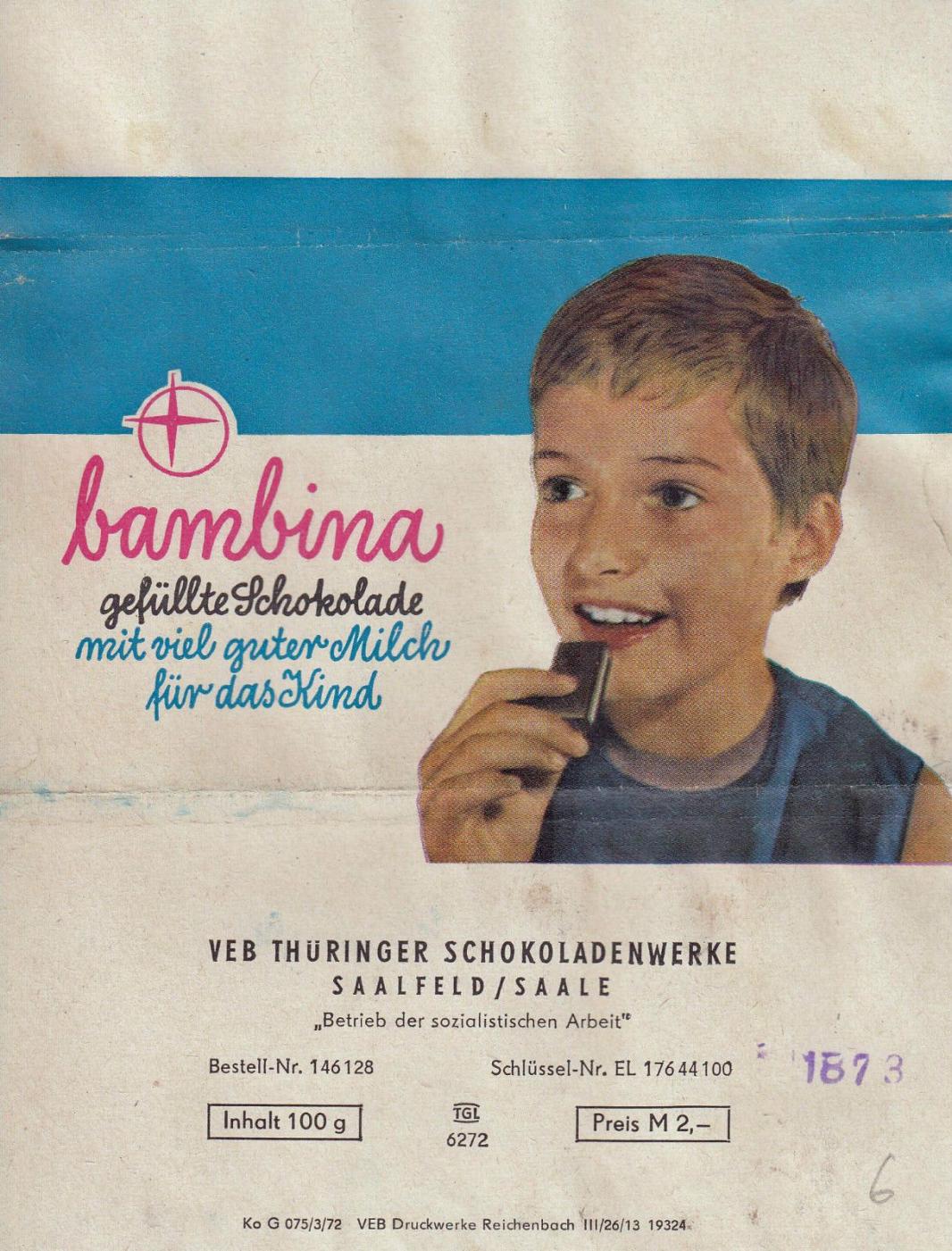
Tafelwerk DDR (Verlag Volk und Wissen)
ganze Arbeit! Und schön, dass es auch kyrillische Zeichen gibt.
Das ist richtig. Nur sah es eben zu beginn mit der Tafelwerk so aus, als habe es die Scvhrift nur als Fotosatz gegeben, und dann hat sich eben die Mode derart geändert, dass solch typische 70er kaum digitalisiert wurden. Natürlich kommt das in die Schrift.
Und wenn Sie mir da beim Kontakt behilflich sein könnten, wär das Schön. Den vorgeachlagenen Copyright-String habe ich jedenfalls schon mal genau so eingefügt und mit dem Einbau auf die Website warte ich natürlich auch noch.
Auch der Fontname steht durchaus noch zur disposition, Tafelwerk war ja mehr als Arbeitstitel gedacht.
Nun, wenn die so schon fetzt, habe ich gedacht, das geht noch fetziger, mit OpenType-Funktionen zum automatischen Durchkoppeln der Worte.
Hier habe ich jetzt die Glyphen in je 4 Varianten:
Als Solozeichen ohne jede Anfangs- und Endstriche,
als Startzeichen ohne Anfangsstrich und Kopplung rechts ,
als mittelzeichen mit beidseitiger Koppelung und
als Endzeichen mit Kopplung lnks und keinem Endstrich.
Ich habe, weil ich dafür so viele rote Striche in meinen Diktaten hatte, auch i-Punkte hinzugefügt - vielleicht ergänze ich das noch als Stilvariante ohne diese - mal sehen.
Wer aber diese Anfangs- und Endstriche wünscht, wie in der Originalversion, einfach Bindestriche vor und nach dem Wort, so lassen sich auch mehrere Worte durchkoppeln.
Tolle Arbeit, Peter. Nur das M gefällt mir persönlich gar nicht. Sieht aus wie ein gedrehtes W, da gefällt mir das der "Scene" besser. Wäre toll wenn Du hier nochmal eine alternative Variante einfügen könntest.
Tafelwerk fetzt. Dieser Name prägt sich ein und ist mehr als treffend. Manch einer von uns musste dieses Buch ja verwenden :-D .
Noch nicht... Aber du könntest ihr ja einen geben :-) - Mein Arbeitstitel ist derzeit "Tafelwerk"
Peter, genau der Gedanke kam mir auch mit dem Titel. Ich staune immer wieder. Die Russische Version find ich auch klasse. Hab mal geschaut was die Übersetzung bringen würde, aber das Wort scheint es nicht als Übersetzung zu geben.
ТАФЕЛВЕРК?
Da hatte man wohl befürchtungen, das man bei "Tafelwerk" an Sprelacart denkt.
nee Peter, Tabellen und Formeln hiess es in den 70ern und später Tafelwerk. Solange es keine Schlagersüßtafel ist, kann man entspannt sein. den Geschmack hab ich heute noch im Mund. Uuulf
möglich dass die von Zetti heute besser schmeckt
oder das hier. wer hier Ähnlichkeit zu einem bestehenden Produkt erkennt...
Da hatte man wohl befürchtungen, das man bei "Tafelwerk" an Sprelacart denkt.
Bei Tafel denke ich immer erst an negative Dinge, Schultafel oder Schlagersüßtafel.
Die Schrift von der Bambina ist gar nicht mal schlecht. Die würde heute noch modern sein. Besser als die spätere Version. (unten) 2Mark war damals verdammt teuer für Kinder
Stimmt. Und ja ich musste auch gleich an Ferrero denken... Vielleicht sollte man Bambina zumindest bei der Kinderschokolade in Wikipedia mit erwähnen, als vergleichbares Produkt.
So kommt man von einem Tafelwerk zum nächsten...
Und ja, grafisch iast die neuere schon witziger, aber bei der Vorstellung des alten Packungsdesign  um die Schreibschrift.
Ich bezog mich eher auf die Typografie. Wann dieses Design erschien kann ich nicht mit Sicherheit sagen.
Ich weiss nur, dass auf der Packung ein Hinweis stand "Design Forchner" (Mädchen mit Kühen)
Edit: Ulrich Forchner ist der Designer/Grafiker